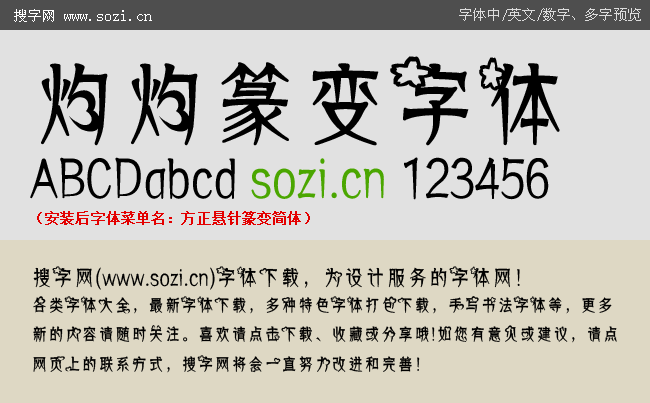
灼灼篆變字體
搜字網(wǎng)給大家提供一款灼灼篆變字體手機中文字體下載。這款手機字體是在方正懸針篆變簡體為原形。然后加入了卡通圖形裝飾,方正懸針篆變字體意在保留篆書韻味,同時將隸書與楷書筆畫特征熔于一爐,端莊秀美、開張疏朗,雍容大氣、復古卻易讀。特別適合喜歡手機字體個性一些的朋友在手機上安裝使用。